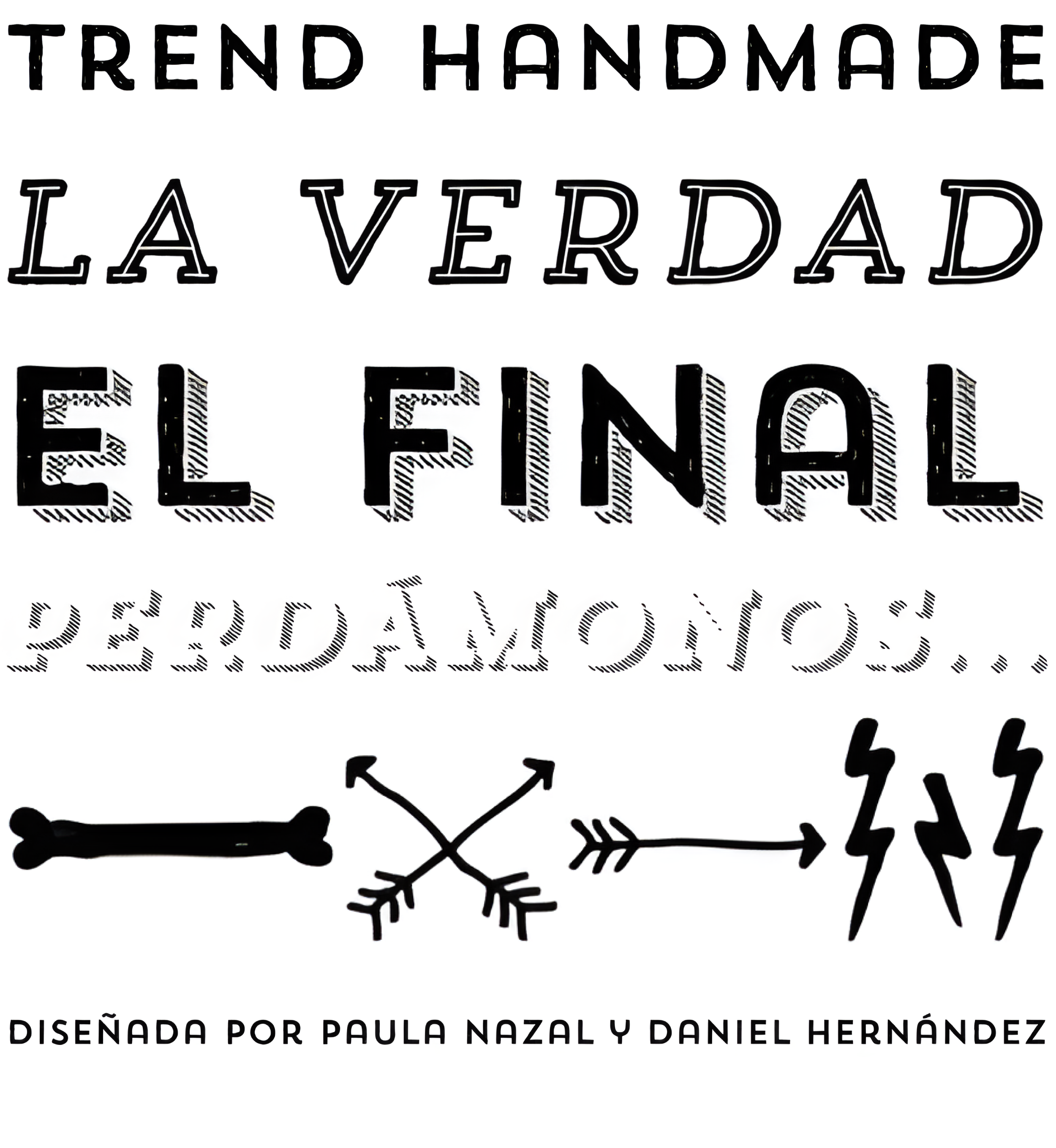
| Descripción | Trend, Trend Handmade es un tipo de letra por capas, tomando como base una fuente sans y una slab. Es el resultado de la observación, búsqueda y estudio de las últimas tendencias mundiales. Trend intenta captar la estética de la moda o incluso la moda misma, integrando elementos de una tendencia muy popular y actual. Es un tipo de letra diseñado para ser utilizado sin necesidad de añadirle nada externo, ya que dispone de todos los componentes necesarios para ello. La tendencia es tendencia. |
| Clasificación | Títulos, Dingbats |
| Familia(s) | Sans One, Sans One Italic, Sans Two, Sans Two Italic, Sans Three, Sans Three Italic, Sans Four, Sans Four Italic, Sans Five, Sans Five Italic, Slab One, Slab One Italic, Slab Two, Slab Two Italic, Slab Three, Slab Three Italic, Slab Four, Slab Four Italic, Slab Five, Slab Five Italic, Ornaments |
| Estilos | 21 |
| Set | Especializado |